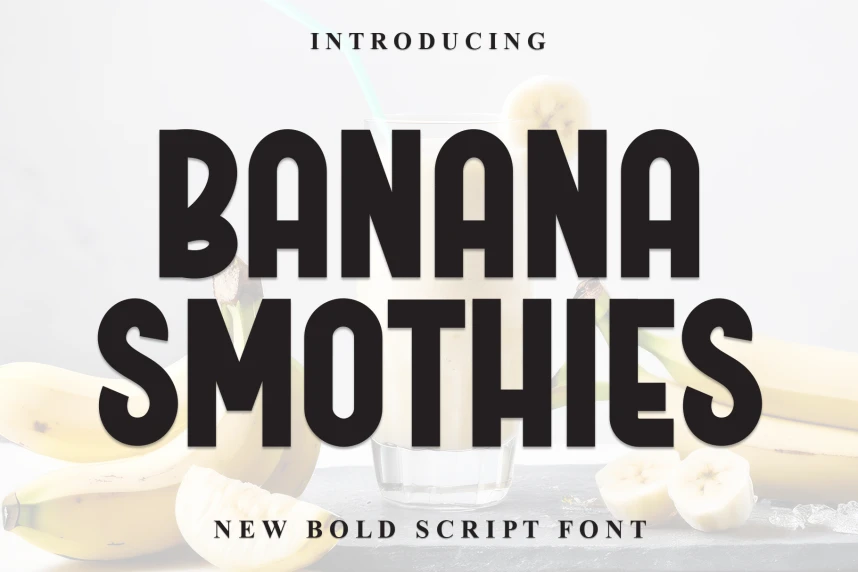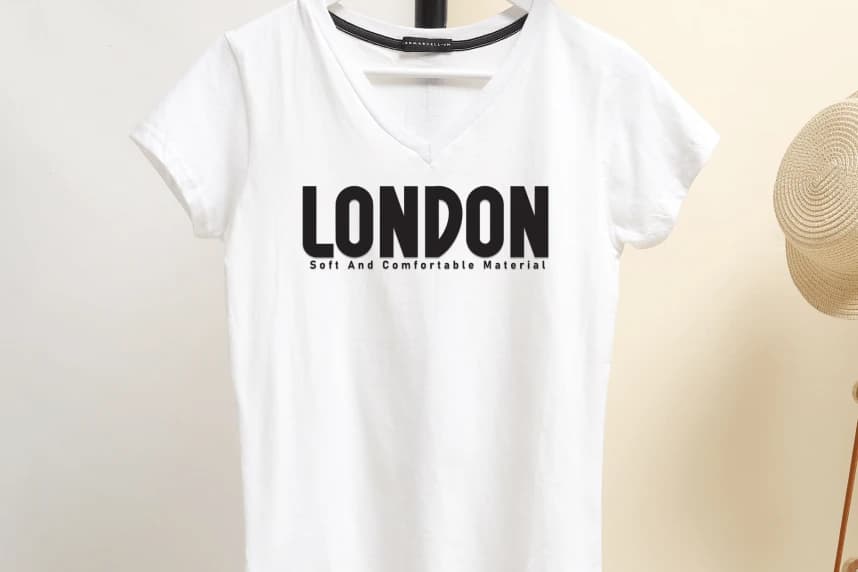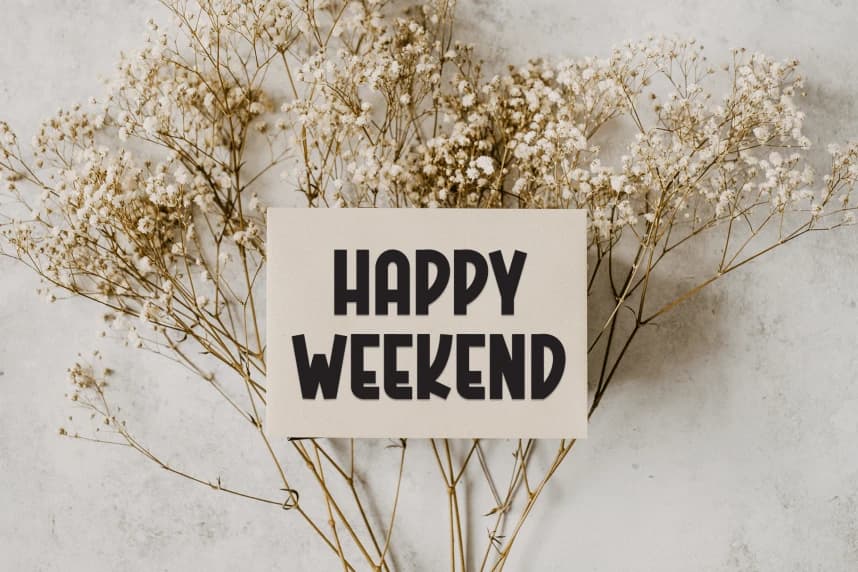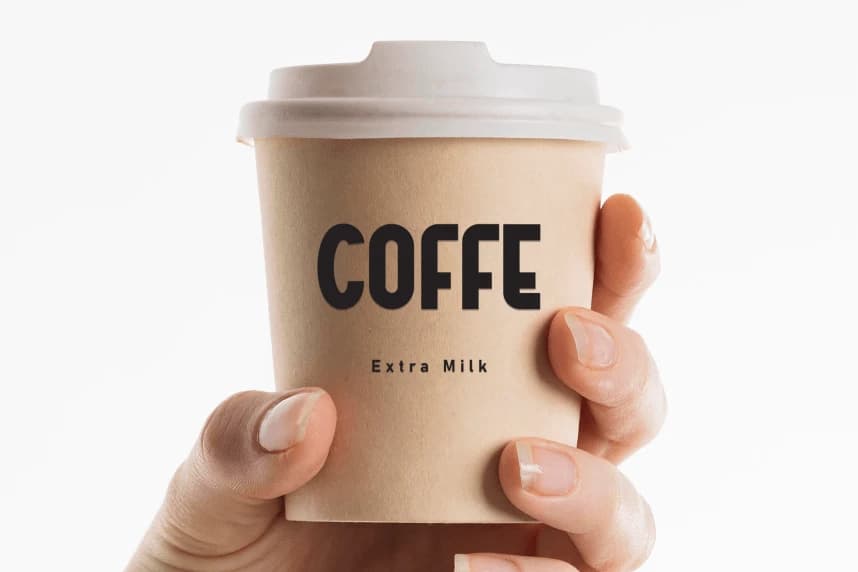
Banana Smothies Display Font
Banana Smothies Display Font tatlı ve samimi bir el yazısı gösterim yazı tipidir. Sevimli ve eğlenceli olan bu font, düğün davetiyelerini, kartları ya da eğlenceli bir dokunuşa ihtiyaç duyabilecek herhangi bir tasarım için idealdir!
Banana Smothies Display Font, tatlı ve dostça bir el yazısı stiline sahip bir gösterişli yazı tipidir. Sevimli ve eğlenceli olan bu font, düğün davetiyeleri, kartlar yazmak veya eğlenceli bir dokunuşa ihtiyaç duyabilecek diğer tasarımlar için idealdir!